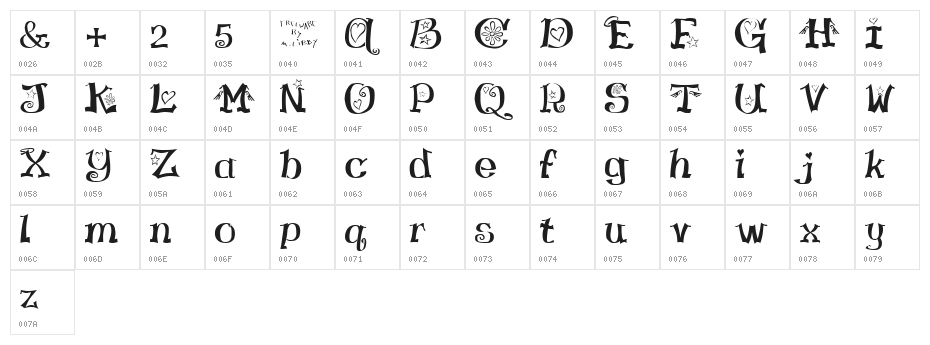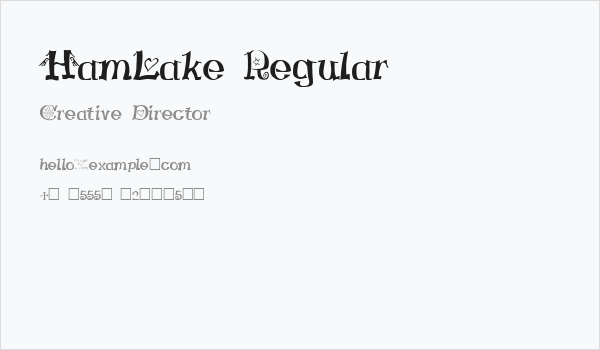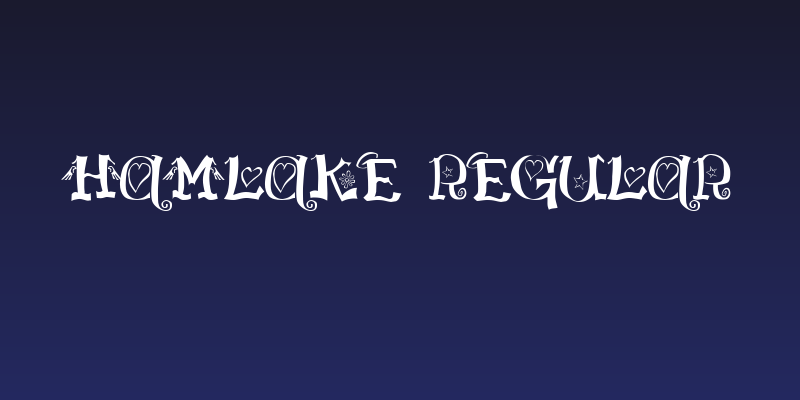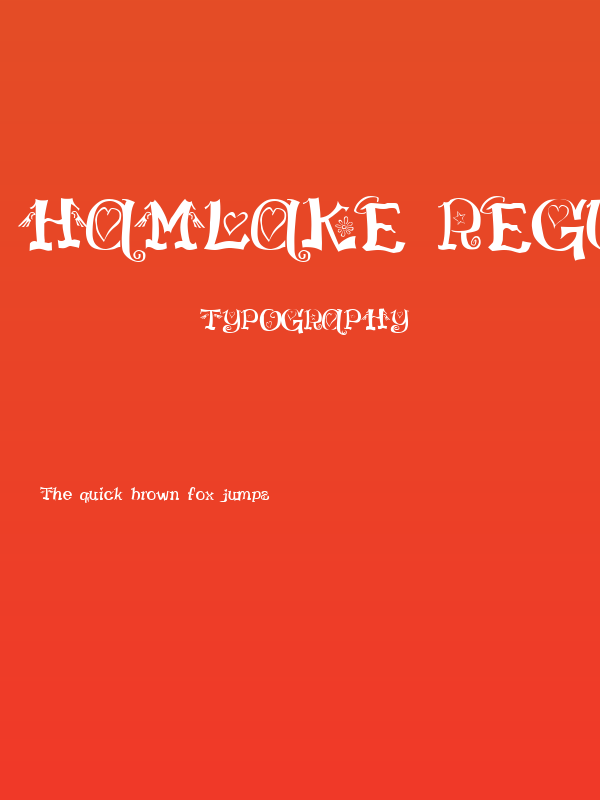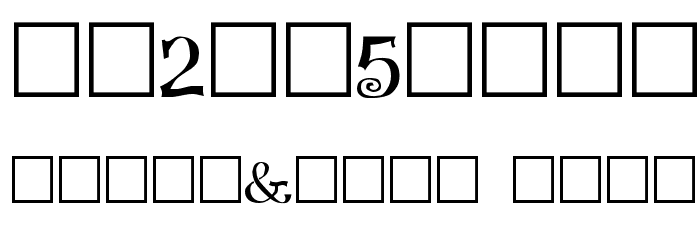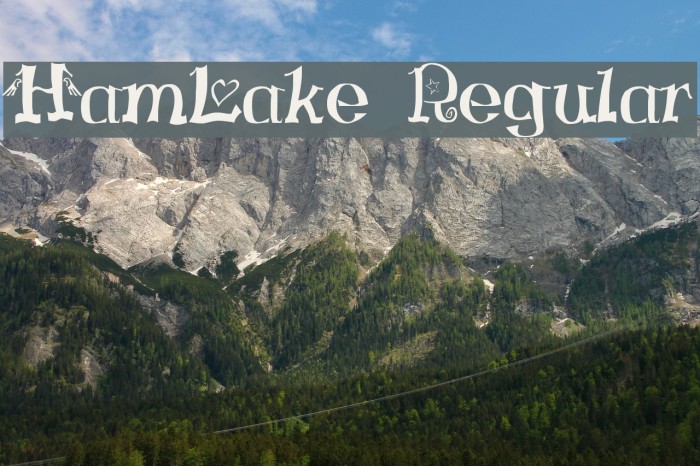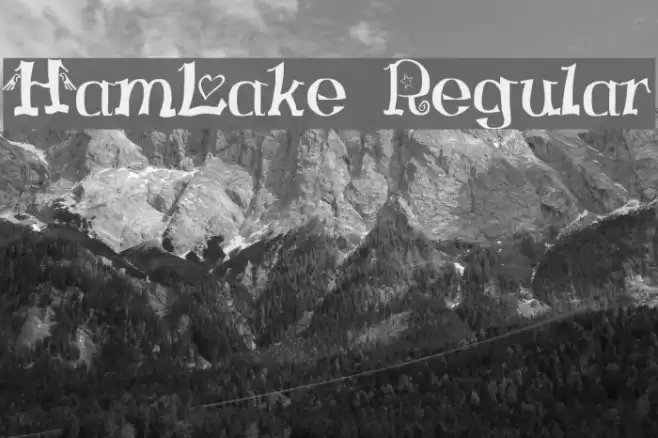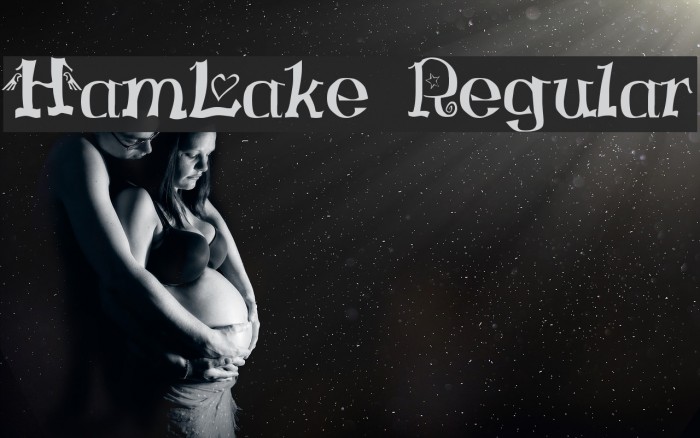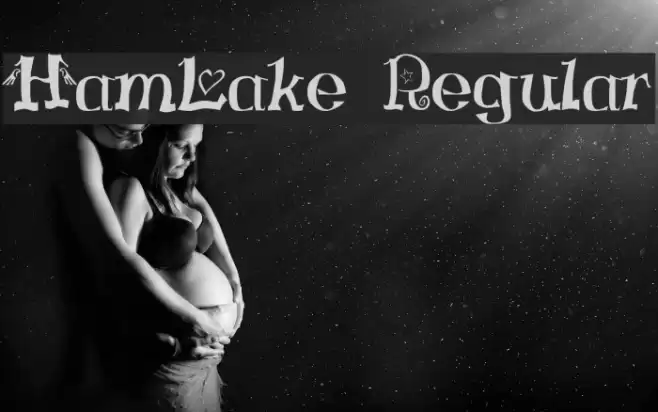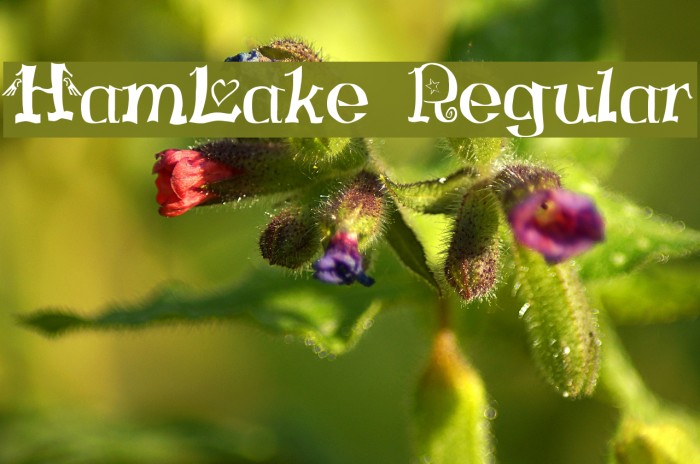
HamLake Regular Font
✎ Decorative
| Категория | Decorative |
| Рекомендуемые проекты | Ideal for children's book covers, playful branding, party invitations, and creative posters. |